Jenis Font dan Contohnya. Elemen visual pertama yang dikenali konsumen adalah font. Mulai dari logo, kemasan, media sosial hingga situs web, jenis font yang Anda gunakan dapat menciptakan berbagai kesan bagi audiens.
Jadi penting bagi Anda untuk mengetahui jenis font dan contohnya. Karena memilih font untuk brand bukan tentang selera, melainkan keputusan yang memengaruhi cara audiens memandang brand Anda.
Berikut ini, MinTiv akan menjelaskan jenis font dan contohnya serta tips memilihnya.
ToggleFont merupakan hal penting untuk brand, karena font yang Anda pilih dapat mencerminkan nilai dan keseluruhan citra brand Anda.
Jika brand Anda berkaitan dengan kesehatan, font yang digunakan harus memberi kesan serius dan dapat diandalkan. Jika menggunakan font yang unik, tidak cocok untuk brand tersebut.
Beberapa personality dari sebuah brand yang umum meliputi fleksibel, formal, santai, tenang, berani, ceria dan hangat. Untuk mewujudkan personality dari brand Anda, maka pilihlah font yang sesuai.
Dalam branding, penggunaan font yang konsisten bisa membantu membangun identitas brand yang kuat. Hal ini dikarenakan jika font terkait dengan suatu brand, bisa menjadi elemen yang mudah diingat dan dikenali oleh audiens.
Berikut ini adalah jenis font dan contohnya untuk brand Anda.
Font serif adalah jenis huruf pertama yang digunakan dalam proses pencetakan skala besar. Berasal dari tahun 1400an, font ini dirancang berdasarkan goresan dekoratif tipis pada ujung goresan suatu karakter.
Hasilnya, font ini menawarkan tampilan klasik dan tradisional. Oleh karena itu, font ini biasanya bisa Anda lihat pada brand yang ingin mempertahankan kemewahan dalam waktu yang lama.
Font serif juga bisa digunakan untuk bisnis yang telah berdiri lama atau memiliki sejarah panjang. Contoh font serif adalah Times New Roman, Garamond, Georgia, Baskerville dan Courier New.
Penggunaan font serif bisa memperkuat identitas brand Anda yang formal, klasik, dan elegan. Brand terkenal yang menggunakan font serif adalah logo Dior, Gap, dan The New York Times.
Jenis font selanjutnya adalah font sans serif, yang serupa tapi tak sama dengan jenis font legend. Perbedaannya yaitu font sans serif memiliki garis di tepi hurufnya yang memberi kesan modern, chic, jujur dan sederhana.
Contoh jenis font ini adalah Helvetica, Roboto, Futura, Calibri dan Lato. Font sans serif bisa menjadi pilihan cocok untuk brand Anda yang memiliki personality modern, bersih, dan user friendly, serta memberi kesan inovatif, relevan, dan mudah didekati. Brand terkenal yang menggunakan font sans serif adalah Chanel, Linkedin, dan Google.
Font skrip merupakan jenis font yang meniru kaligrafi atau tulisan tangan kursif. Namun, memilih font ini juga beresiko untuk brand Anda karena cenderung sulit dibaca dan bisa saja memberi kesan ketinggalan zaman. Meski begitu, jika Anda menggunakannya dengan sesuai brand Anda bisa tampak unik seperti tulisan merek Coca-cola, Barbie dan Ford.
Contoh font jenis ini adalah Harlend, Zapfino, Brush Script, Lobster dan Pacifino. Jika brand Anda ingin menciptakan kesan hangat, eksklusif, atau kreatif maka font ini bisa menjadi pilihan.
Jenis font ini sesuai dengan namanya, meniru tulisan tangan manusia. Hal ini memberi kesan yang lebih personal dan mudah dipahami untuk brand apapun.
Contoh font handwriting seperti Bradley Hand dan Vivaldi. Brand yang menggunakan font ini tampak unik seperti H&M, Virgin, dan Ray-Ban. Jika brand Anda merupakan hasil buatan tangan maka bisa menggunakan font ini.
Jenis font ini memiliki gaya yang paling beragam. Font dekoratif sangat bergaya dengan dan menggunakan berbagai bentuk dan proporsi. Contoh font jenis ini adalah Gazpacho, Abril Fatface, Gilroy, Bourton font dan Cooper Black.
Penggunaan font dekoratif juga cocok untuk brand Anda yang ingin mudah diingat dan khas. Brand yang menggunakan font ini contohnya Toys R Us, Disney dan Subway.
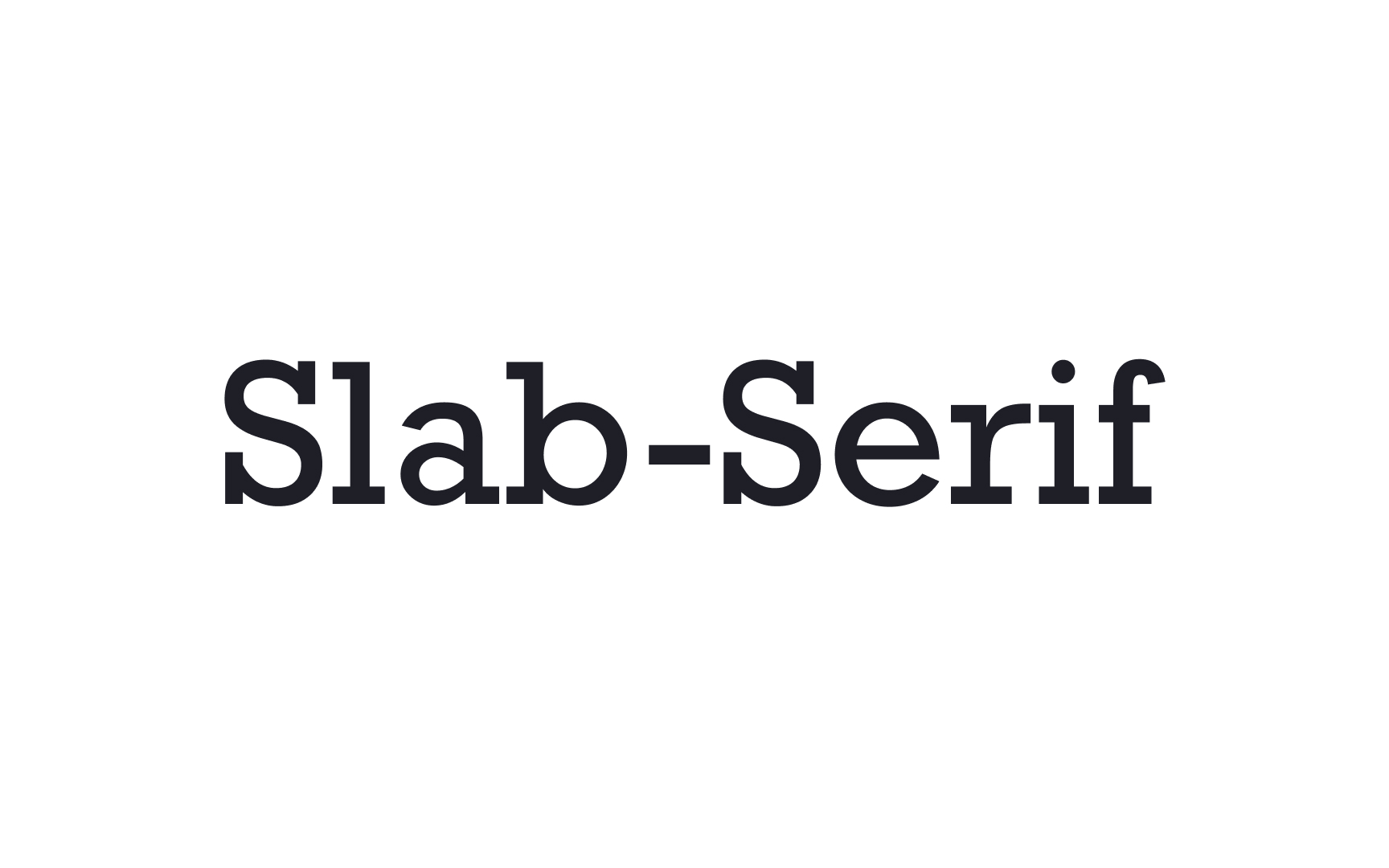
Ini merupakan jenis font versi serif yang besar dan kotak-kotak. Font ini sering digunakan untuk judul berita, font tampilan dan apapun yang memerlukan font tebal untuk penekanan. Contoh font ini adalah Rockwell, Roboto Slab, Courier, Memphis, Museo Slab, Arvo, dan Clarendon.
Brand terkenal yang menggunakan jenis font ini adalah Sony, Honda dan Volvo. Jika Anda ingin menciptakan brand dengan kesan kuat, profesional, dan mudah dikenali, maka font ini bisa menjadi pilihan.
Setelah mengetahui jenis font dan contohnya, berikut ini ada tips memilih font untuk brand Anda.
Font yang Anda pilih harus sesuai dengan brand personality. Cara untuk memahami ini adalah dengan meneliti font yang digunakan oleh brand yang sama dengan Anda.
Anda tidak harus menggunakan font yang sama, tetapi ini bertujuan untuk mendapatkan gambaran umum tentang font apa yang kemungkinan cocok dengan brand yang Anda miliki.